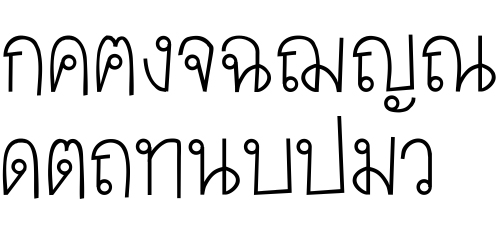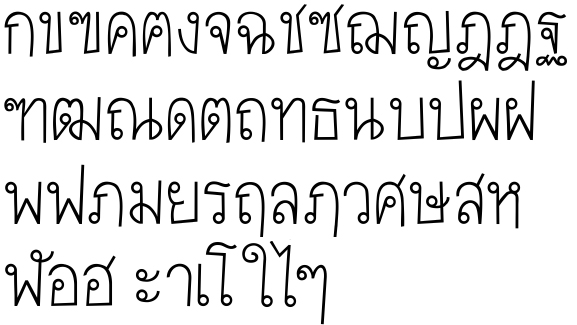
ฟอนต์ใหม่ค่ะ.. (ไม่มีชื่อ)
ตอนนี้กำลังทำฟอนต์ตัวใหม่อยู่ (ยังคิดชื่อไม่ได้)
ทำไปได้ไม่กี่ตัว ก็รู้สึกว่าฟอนต์มันโหลๆ
จะถามว่ามันไปซ้ำหรือคล้ายๆกับฟอนต์ตัวไหนรึเปล่าคะ
ถ้าซ้ำจะได้ไม่ทำต่อ  :08:
แล้วก็ช่วยติชมด้วยค่ะ
สวยๆๆๆ
ทำต่อเลยจ้ะ จะได้มีให้เลือกหลายๆแบบ
พี่พีชเก่งอะ
ทั้งเก่ง ทั้งน่ารักเลย ทั้งสูงด้วย
ทำเลยๆๆๆ  :12:
ไม่ซ้ำครับ :12:
และสวยมากจนน่าสนับสนุนแรงๆ
พีชทำอันนี้แล้วขยันเอามาโชว์ความคืบหน้านะ
พี่ๆ น้องๆ ลุงๆ ป้าๆ จะช่วยกันเกลาให้
แล้วจะมารายงานความคืบหน้าเป็นระยะๆ   :22:
ลายมือสวยมากครับ  :33:
ลายมือน่ารักดี
ส่วนตัวนะ วาฬว่า
จ จานด้านบนมันมีจุดสะดุด ท ทหารด้วยนิดหน่อย ตัวอื่นๆมันจะโค้งลื่นไหล
แต่ไม่ได้โดดมาก ถ้าชอบแล้วไม่ต้องแก้ก็ได้
ง งู ดูป่องๆ แต่ก็น่ารักดี ป่องแล้วตัวจะได้ไม่เอนด้วย
เนื่องจาก ง งู มันป่อง วาฬเสนอชื่อ "เบนโล"
นึกถึงนิทานเด็ก
ลองทำแซมเปิ้ลมาสักประโยค
เอามาประกอบรูปนิทานเด็กสักชิ้นสิ
เหมาะมากเลย  :25:
ทำภาษาไทยเสร็จซะที
เหนื่อยจริงๆ  :08:
ช่วยติชมให้ด้วยนะคะ   :22:
มีกลิ่นของ GMO อยู่ด้วย   :42: